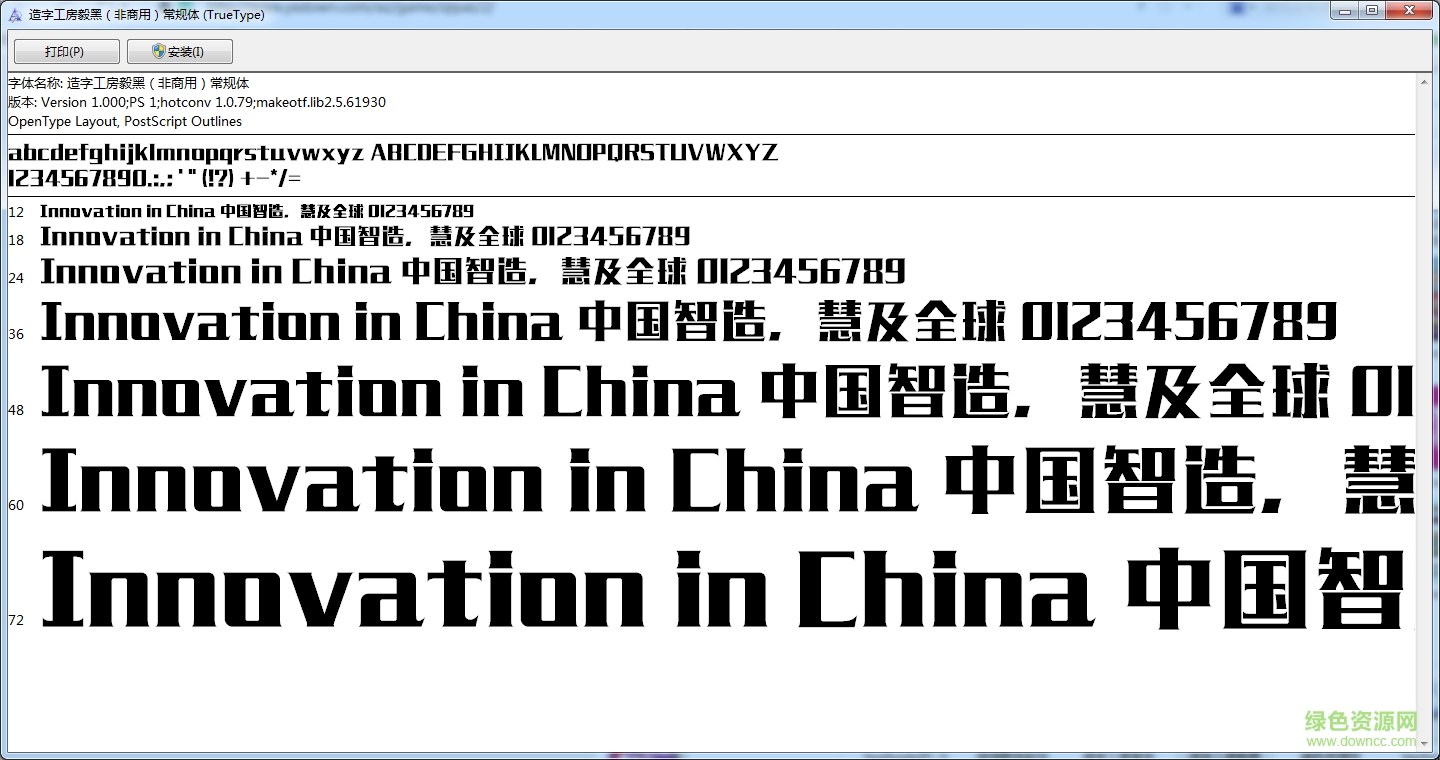
mfyihei字體
mfyihei是什么字體?mfyiheinoncmmercial regular字體又叫造字工房毅黑(非商用)常規(guī)體,筆畫粗曠,堅(jiān)毅有型,給人的感覺是充滿力量感,使用效果非常醒目,歡迎大家免費(fèi)下載!
mfyihei regular特點(diǎn)
1.適用于文字標(biāo)題、廣告設(shè)計(jì)、企業(yè)宣傳等視覺環(huán)境,有著極強(qiáng)的應(yīng)用空間;
2.細(xì)膩出彩的筆畫特點(diǎn)讓字形整體更加剛毅,灑脫而靈動(dòng),且具有極強(qiáng)的時(shí)尚感;
3.整體風(fēng)格粗曠厚重、主次筆畫處理極其鮮明、結(jié)構(gòu)方正均衡;